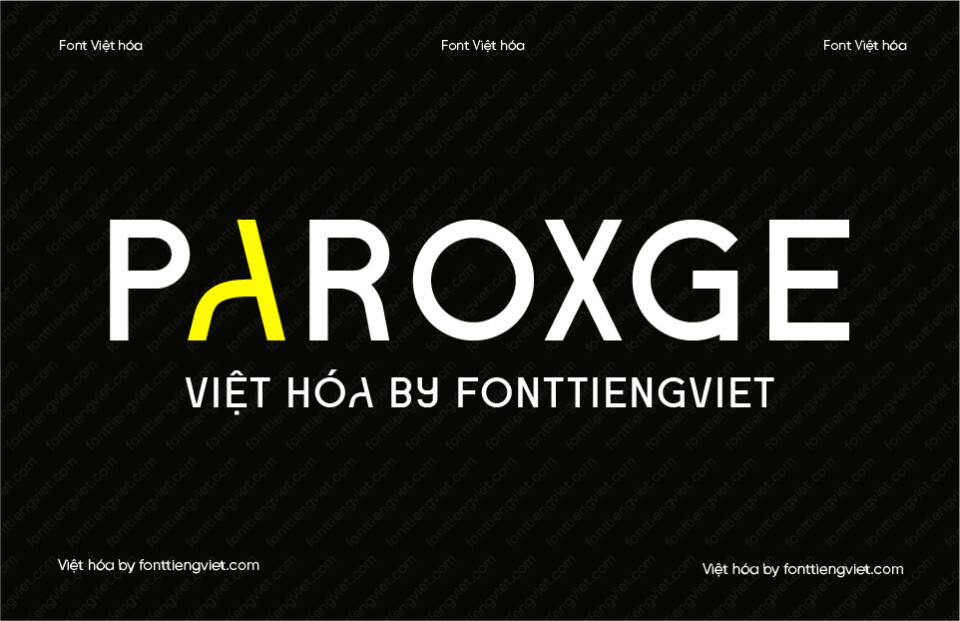
Font Việt hóa 1FTV Paroxge
Giới thiệu về Font Việt hóa 1FTV Paroxge
Trong thế giới đồ họa hiện đại, việc tìm kiếm một bộ Font Miễn Phí chất lượng và hỗ trợ đầy đủ tiếng Việt luôn là ưu tiên hàng đầu của các nhà thiết kế. Font Việt hóa 1FTV Paroxge nổi lên như một hiện tượng nhờ sự kết hợp độc đáo giữa phong cách cổ điển và hơi thở đương đại. Đây là bộ font chữ không chỉ mang lại vẻ đẹp thẩm mỹ cao mà còn đảm bảo tính ứng dụng linh hoạt trong nhiều loại hình dự án khác nhau. Được đội ngũ 1FTV tỉ mỉ chỉn chu từng đường nét, bộ font này đã giải quyết triệt để vấn đề lỗi dấu thường gặp, giúp người dùng tại Việt Nam tự tin thể hiện ý tưởng sáng tạo mà không gặp bất kỳ rào cản kỹ thuật nào.
Những đặc điểm nổi bật của Font Việt hóa 1FTV Paroxge
Thiết kế độc đáo và hiện đại
Điểm thu hút đầu tiên của Font Việt hóa 1FTV Paroxge chính là cấu trúc hình học cân đối nhưng không kém phần phá cách. Các ký tự được tạo hình với độ dày vừa phải, tạo cảm giác thanh thoát nhưng vẫn rất vững chãi. Sự tinh tế trong cách xử lý các góc bo tròn và những đường cắt sắc sảo giúp bộ font này có một diện mạo rất riêng biệt. Đối với các bạn học sinh và sinh viên, việc sử dụng font chữ này trong các bài thuyết trình hay thiết kế báo tường sẽ tạo nên một điểm nhấn chuyên nghiệp, giúp nội dung trở nên lôi cuốn và dễ tiếp nhận hơn đối với người xem.
Khả năng ứng dụng đa dạng trong thực tế
Không chỉ dừng lại ở các ấn phẩm in ấn, Font Việt hóa 1FTV Paroxge còn cực kỳ hiệu quả khi hiển thị trên các nền tảng kỹ thuật số. Bạn có thể sử dụng nó cho các tiêu đề website, ảnh bìa mạng xã hội, hay thậm chí là thiết kế logo cho các dự án khởi nghiệp nhỏ. Trong môi trường học đường, giáo viên có thể dùng font chữ này để thiết kế các slide bài giảng sinh động, giúp học sinh hứng thú hơn với bài học. Sự rõ ràng của các mặt chữ giúp việc đọc văn bản dài không gây mỏi mắt, đây là một điểm cộng rất lớn mà không phải bộ font nghệ thuật nào cũng có thể đáp ứng được.
Cách tối ưu hóa Font Việt hóa 1FTV Paroxge trong trình bày
Để phát huy tối đa vẻ đẹp của Font Việt hóa 1FTV Paroxge, người dùng nên chú ý đến việc kết hợp màu sắc và khoảng cách chữ (kerning). Khi sử dụng cho tiêu đề lớn, bạn có thể tăng nhẹ khoảng cách giữa các chữ cái để tạo cảm giác sang trọng và thoáng đãng. Ngược lại, khi dùng cho các đoạn văn ngắn, hãy giữ nguyên định dạng mặc định để đảm bảo tính dễ đọc. Ngoài ra, việc kết hợp Paroxge với một font chữ không chân (sans-serif) đơn giản khác sẽ tạo nên một sự tương phản tuyệt vời, giúp phân cấp thông tin một cách khoa học và logic nhất cho người đọc.